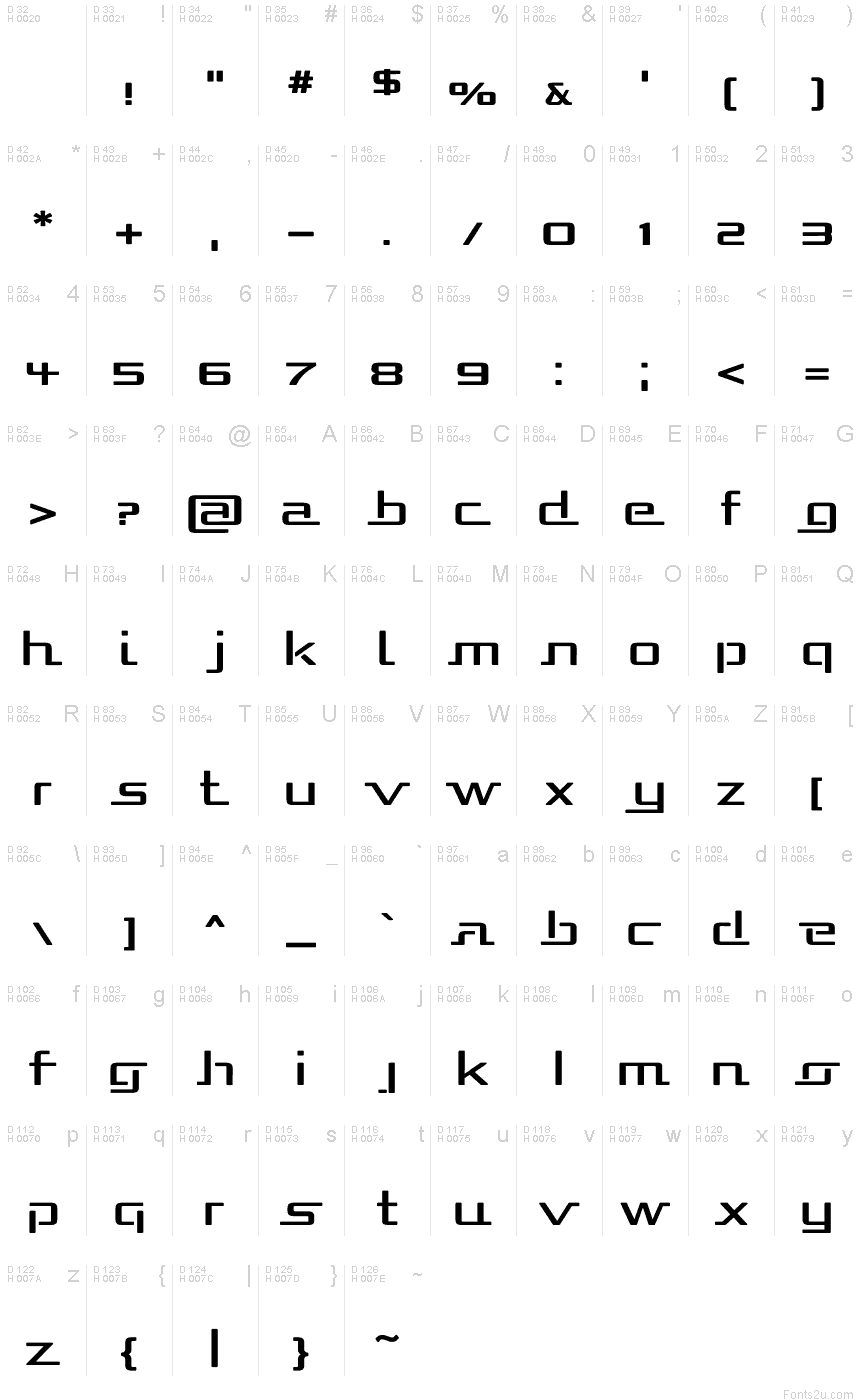
Republika Exp
Republika Exp od Apostrophe to darmowy, futurystyczny krój typu display o eleganckim, technologicznym rytmie. Jego znaki zbudowane są z grubych, równych kresek przechodzących w miękkie, kwadratowe narożniki. Nadaje to alfabetowi płynność kojarzącą się z obwodami, a otwarte kształty i wydłużone poziome linie sprawiają, że całość jest lekka, chłodna i syntetyczna.
Ten darmowy font najlepiej sprawdza się tam, gdzie pożądany jest kontrolowany klimat sci-fi – w grafice interfejsów, oprawie muzycznej, nagłówkach plakatów, brandingu gier i krótkich animowanych planszach tytułowych. Świetnie nadaje się również do logotypów i zwartych nagłówków, ponieważ zaokrąglone, prostokątne formy sprawiają, że nawet krótkie słowa wyglądają na precyzyjnie zaprojektowane i spójne.